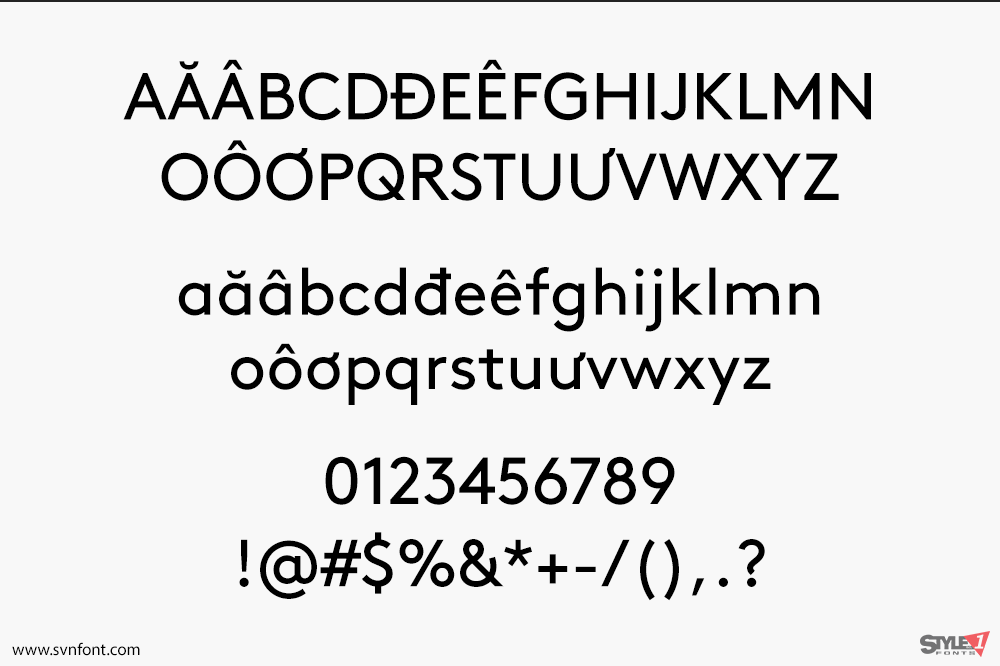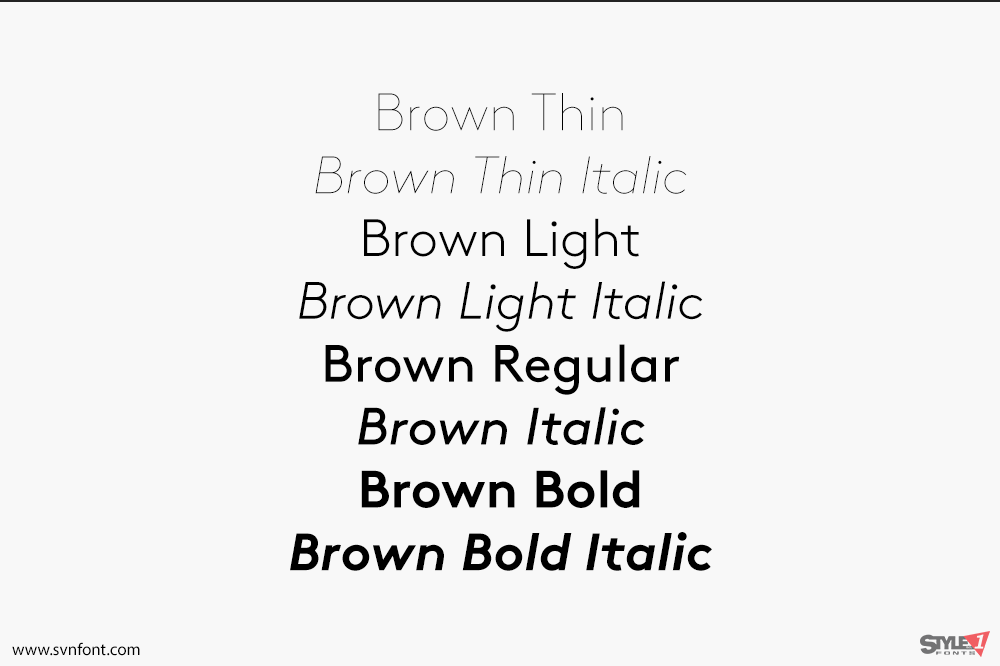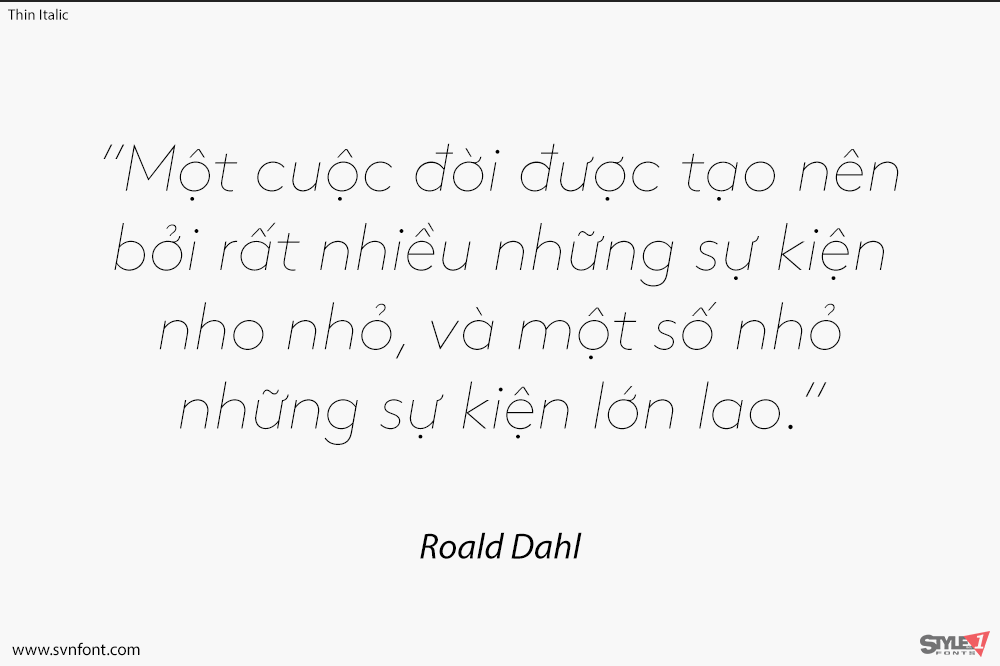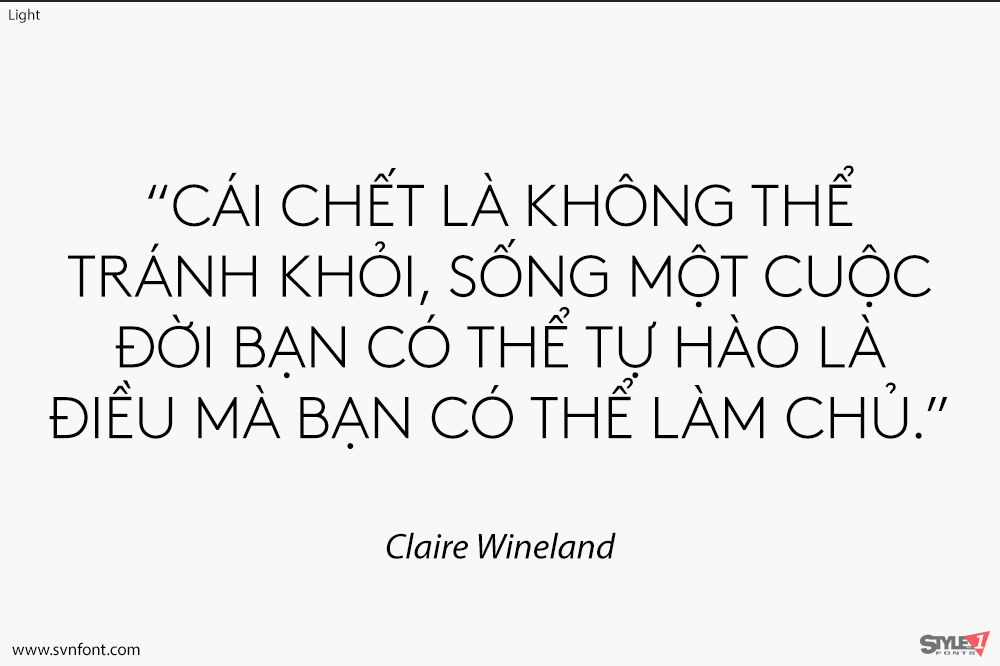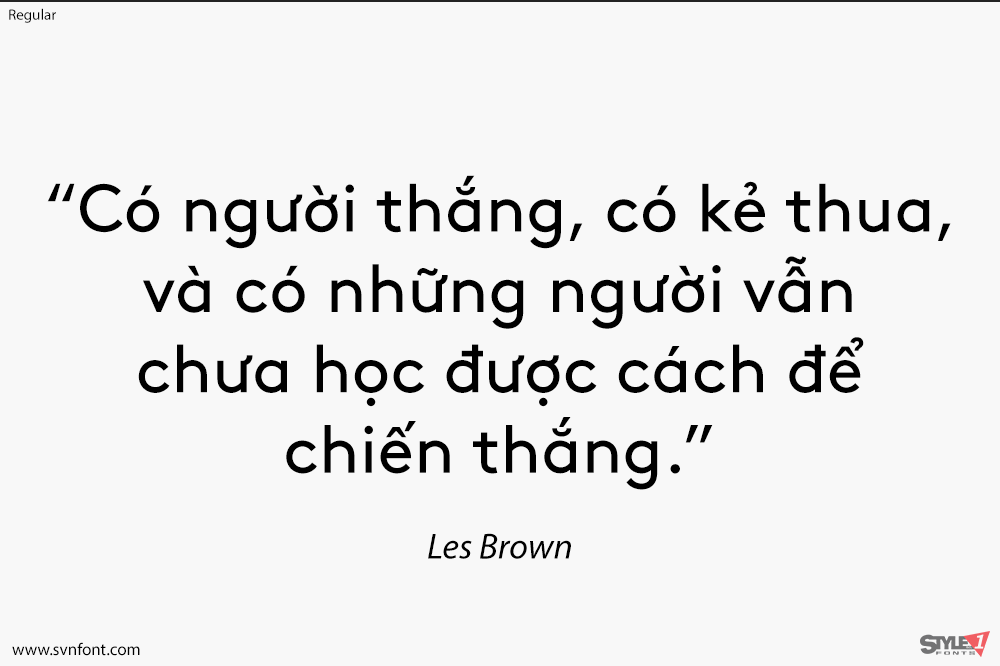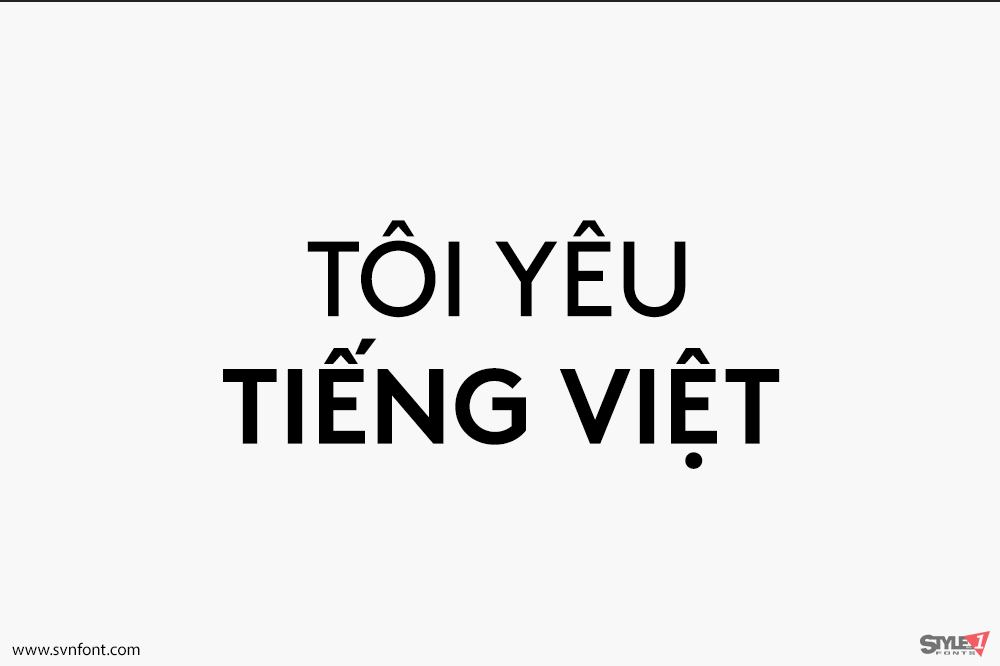
LL Brown mang ơn rất nhiều công trình đột phá của cả Edward Johnston và Arno Drescher, với các thiết kế tương ứng của họ – Johnston Sans (1916) và Super Grotesk (1930) – về mặt lịch sử nằm trong số những kiểu chữ sans serif hình học có ảnh hưởng nhất.
Công ty Đường sắt Điện ngầm Luân Đôn (Underground Electric Railways Company of London) đã đặt hàng Johnston Sans, và sau khi được chấp nhận làm kiểu chữ doanh nghiệp cho tất cả các phương tiện giao thông công cộng của Luân Đôn vào năm 1933, kiểu chữ này vẫn được sử dụng cho đến ngày nay.
Super Grotesk ban đầu ít thành công hơn, nhưng nó đã đạt được thành công đáng kể ở Cộng hòa Dân chủ Đức (GDR) sau Thế chiến thứ hai, cuối cùng trở thành một trong những kiểu chữ được sử dụng rộng rãi nhất ở Đông Đức.